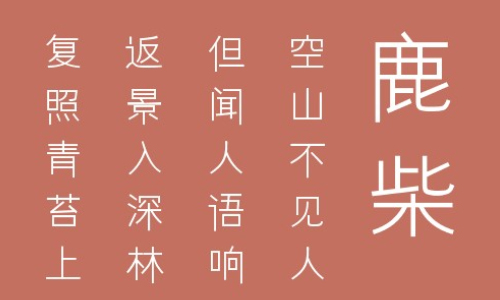
往后狗生請(qǐng)指教字體是XFont字庫(kù)中的一款個(gè)性字體,該字體書寫的非常認(rèn)真,橫平豎直,筆畫中沒有勾畫與彎曲,能夠應(yīng)用于文本裝潢、信息展示、網(wǎng)頁(yè)設(shè)計(jì)、篆刻制模、數(shù)據(jù)制作、裝潢設(shè)計(jì)、計(jì)算藝術(shù)設(shè)計(jì)、視覺設(shè)計(jì)、字帖等一切合法應(yīng)用場(chǎng)景,歡迎大家前來下載。